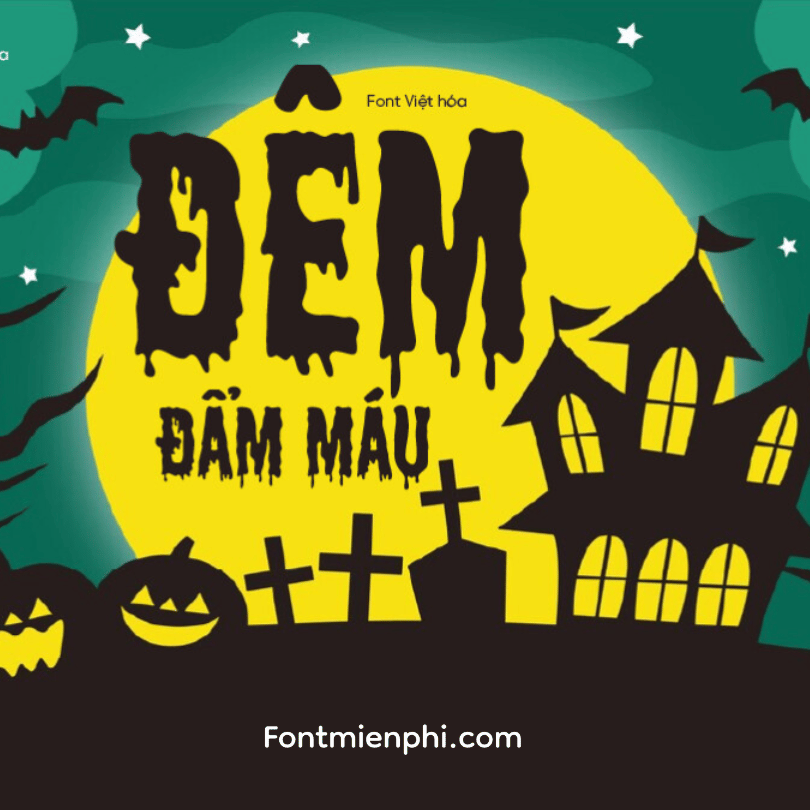
Font Việt hóa 1FTV VIP Shlop ,font Font Halloween – Phông Chữ Halloween “Kinh Dị Pha Chút Hài Hước”
- Font chữ độc đáo với phong cách “ma quái nhưng vui nhộn”
- Hỗ trợ đầy đủ bảng mã Unicode tiếng Việt
- Thiết kế nét chữ “nhếch nhác” có chủ đích, kết hợp yếu tố kinh dị và hài hước
Phong cách thiết kế đặc biệt:
✓ Nét chữ loang lổ như máu khô
✓ Các chi tiết ma quái được cách điệu vui nhộn
✓ Hiệu ứng “nhòe mực” tạo cảm giác bí ẩn
✓ Kèm 3 phiên bản: Regular, Bold và Distressed
Ứng dụng sáng tạo:
① Thiết kế poster Halloween cho gia đình
② Làm áo thun, sticker hài hước dịp Halloween
③ Thiết kế menu quán café theme ma quái
④ Làm banner sự kiện Halloween vui nhộn
Ưu điểm vượt trội:
- Dễ đọc nhưng vẫn giữ được chất Halloween
- Phù hợp cả thiết kế kinh dị lẫn hài hước